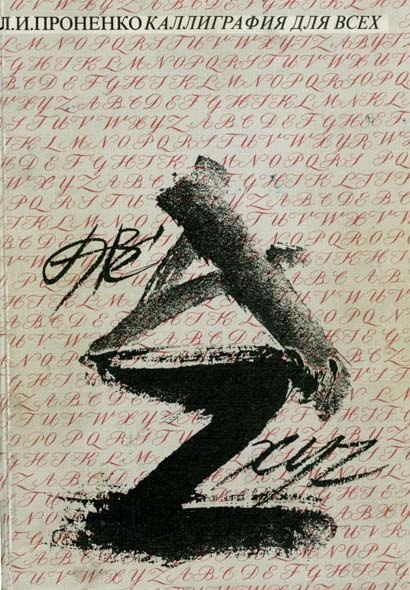
«Каллиграфия для всех», Леонид Проненко
«Каллиграфия для всех» – книга об искусстве писать красиво. Автор знакомит читателей с краткой историей каллиграфии, стремится увлечь их искусством письма и помочь овладеть шрифтовой культурой. Издание богато иллюстрировано – в него вошли произведения известных художников многих стран, в том числе ранее не публиковавшиеся, которые заинтересуют и новичков, и мастеров шрифта.
Книга адресована широкому кругу читателей, но в первую очередь – художникам, дизайнерам, иллюстраторам и шрифтовикам.